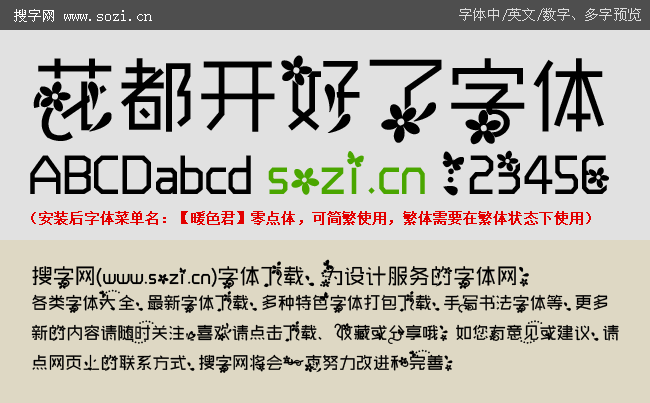
花都開好了字體
搜字網(wǎng)給大家提供一款花都開好了字體手機(jī)中文字體下載。這款手機(jī)字體是將黑體字體進(jìn)行重新設(shè)計(jì),更加具有藝術(shù)感,字體間又嵌入了了漂亮的花朵圖案。是一款非常藝術(shù)的字體,特別適合喜歡手機(jī)字體個(gè)性一些的朋友在手機(jī)上安裝使用。